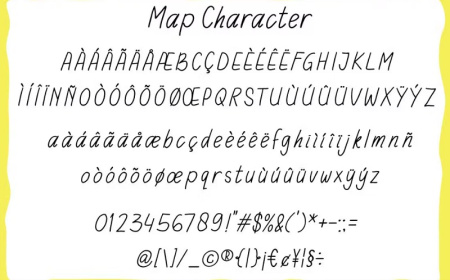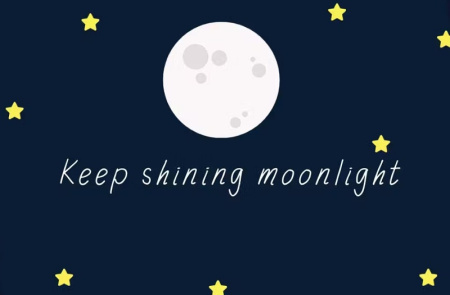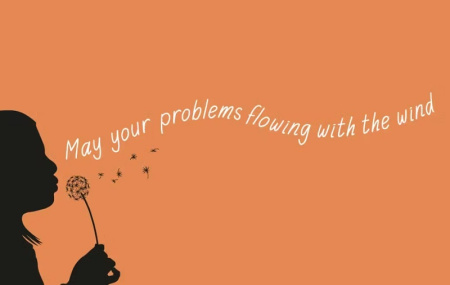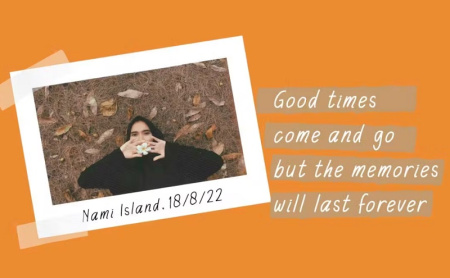
دانلود فونت انگلیسی کتابی Joy Notebook
دانلود فونت انگلیسی کتابی Joy Notebook یک فونت دست نویس ساده است که به طرح های شما حس دست ساز معتبری می دهد. فونت انگلیسی Joy Notebook برای لوازم التحریر، لوگوها، رسانه های اجتماعی یا تقریباً هر چیزی که به آن لمس دست نویس نیاز دارد، عالی است. برای دانلود این فونت از جی اف ایکس دانلود در ادامه مطلب با ما همراه باشید.
✅ نام فونت انگلیسی: Joy Notebook
✅ فونت نوت بوک Joy شامل حروف بزرگ و کوچک
✅ پشتیبانی از چند زبان (لاتین اروپای غربی)،
✅ اعداد و علائم نگارشی